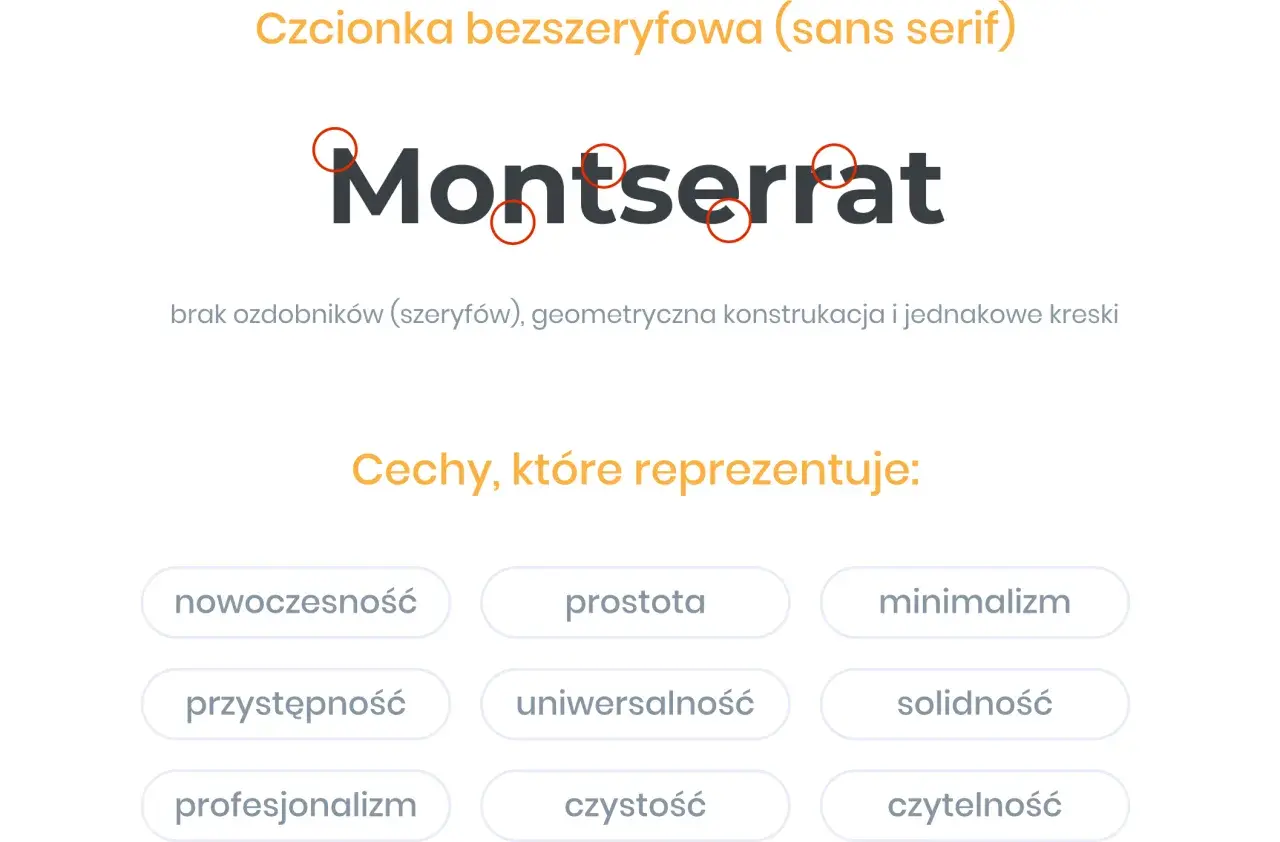
Typografia może podnieść wiarygodność marki albo osłabić ją w kilka sekund. W reklamie lokalnej, na stronie firmowej czy w menu restauracji decyduje nie tylko treść, ale też to, jak litery prowadzą wzrok i czy komunikat da się odczytać bez wysiłku. W praktyce właśnie od tego zależy dobór kroju czcionki, a nie od samego gustu projektanta. W tym tekście rozkładam temat na konkretne części: czym jest krój pisma, jak wpływa na odbiór marki, jak dobrać go do nośnika i jak uniknąć błędów, które psują czytelność.
Najważniejsze rzeczy, które warto wiedzieć, zanim wybierzesz krój do projektu
- Krój pisma nadaje tekstowi charakter, ale musi przede wszystkim pozostać czytelny.
- W reklamie lokalnej najlepiej sprawdzają się zwykle proste, wyraźne fonty z dobrą rozpoznawalnością w małym formacie.
- Jedna marka rzadko potrzebuje więcej niż 2 kroje w tym samym projekcie.
- Na ekranie i w druku obowiązują inne warunki, więc ten sam projekt trzeba oceniać osobno w obu środowiskach.
- Najczęstszy błąd to wybieranie efektownych liter kosztem szybkości odczytu.
Czym różni się krój pisma od fontu i dlaczego to ma znaczenie
W codziennym języku te pojęcia często się mieszają, ale w typografii różnica jest przydatna. Krój pisma to zaprojektowany zestaw liter o wspólnej stylistyce, natomiast font jest jego konkretną cyfrową odmianą, na przykład w określonej grubości, wersji i formacie pliku. Dla osoby zamawiającej reklamę nie jest to akademicki detal, tylko praktyczna wskazówka: wybierasz nie „ładne literki”, lecz narzędzie, które ma działać w konkretnym miejscu i rozmiarze.
Warto też pamiętać, że w projektach marketingowych liczy się cały system typograficzny, a nie pojedyncza nazwa fontu. Ten sam krój może wyglądać dobrze w nagłówku, ale fatalnie w małym akapicie. Inny świetnie sprawdzi się na wizytówce, lecz na szyldzie okaże się zbyt delikatny. Gdy rozumiesz tę różnicę, łatwiej podejmujesz decyzje, które nie kończą się poprawkami po wydruku.
To prowadzi do najważniejszego pytania: jaki efekt ma wywołać tekst, zanim jeszcze ktokolwiek zacznie go czytać?
Jak typografia zmienia odbiór marki i reklamy
Typografia nie tylko „ładnie wygląda”. Ona komunikuje tempo, ton i poziom formalności. Krój z szeryfami może budować skojarzenie z tradycją, zaufaniem i stabilnością, a prosty bezszeryfowy zwykle brzmi nowocześniej, czyściej i bardziej neutralnie. To nie są sztywne reguły, ale w praktyce często działają właśnie tak, szczególnie gdy odbiorca widzi projekt tylko przez kilka sekund.
W reklamie lokalnej to ma ogromne znaczenie. Inaczej projektuje się komunikat dla kancelarii, inaczej dla salonu beauty, a jeszcze inaczej dla warsztatu samochodowego czy kawiarni. Na witrynie czy banerze przy ruchliwej ulicy czytelność wygrywa z ozdobnością. Z kolei w logo albo krótkim haśle można pozwolić sobie na więcej charakteru, o ile nie psuje to rozpoznawalności.
Ja zwykle zaczynam od pytania, co klient ma poczuć po pierwszym kontakcie z marką: bezpieczeństwo, energię, prestiż, a może po prostu prostotę. Dopiero potem dobieram krój, bo litery nie są dekoracją oderwaną od przekazu. Są jego częścią.
Gdy ta zależność jest jasna, łatwiej przejść od ogólnej teorii do konkretnych rodzajów krojów i ich zastosowań.
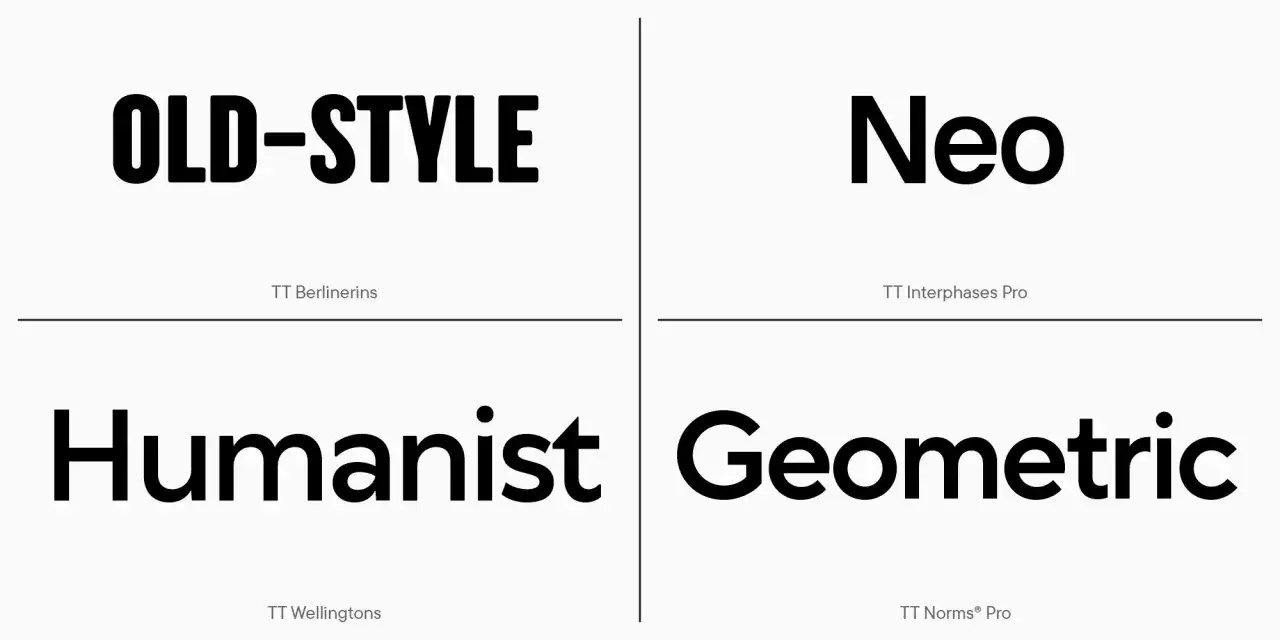
Rodzaje krojów i kiedy każdy z nich ma sens
Najprościej podzielić kroje według ich charakteru i sposobu użycia. W praktyce nie chodzi o to, by znać wszystkie nazwy, tylko wiedzieć, czego się po nich spodziewać.
| Rodzaj | Jak wygląda | Kiedy działa najlepiej | Na co uważać |
|---|---|---|---|
| Szeryfowy | Ma drobne zakończenia przy literach, wygląda bardziej klasycznie. | Marki premium, treści redakcyjne, komunikacja oparta na zaufaniu i tradycji. | W małych rozmiarach lub przy niskiej jakości druku może tracić wyrazistość. |
| Bezszeryfowy | Jest prostszy, czystszy i często bardziej geometryczny. | Strony internetowe, social media, szyldy, ulotki i komunikaty usługowe. | Przy źle dobranej grubości bywa zbyt neutralny i „bez twarzy”. |
| Płytowy | Ma masywniejsze szeryfy, daje mocny, stabilny efekt. | Nagłówki, reklamy z charakterem, marki, które chcą wyglądać solidnie. | W długim tekście może męczyć wzrok, jeśli jest zbyt ciężki. |
| Skryptowy | Naśladuje pismo odręczne, bywa elegancki lub romantyczny. | Logotypy, zaproszenia, pojedyncze hasła, elementy dekoracyjne. | W dłuższym tekście prawie zawsze przegrywa z czytelnością. |
| Display | Stworzony do przyciągania uwagi, często ma mocny charakter. | Plakaty, kampanie sezonowe, krótkie hasła, grafiki promocyjne. | To krój „na efekt”, więc łatwo przesadzić i przeciążyć projekt. |
| Monospace | Każda litera zajmuje podobną szerokość, wygląda technicznie. | Elementy kojarzone z technologią, kodem, danymi lub nowoczesnym minimalizmem. | W marketingu trzeba go używać oszczędnie, bo szybko dominuje kompozycję. |
Jeśli miałbym wskazać najbezpieczniejszy punkt startu dla lokalnej firmy, wybrałbym prosty bezszeryfowy krój do treści i ewentualnie mocniejszy wariant do nagłówków. Z kolei dekoracyjne litery zostawiłbym do krótkich akcentów, bo ich siła polega na tym, że pojawiają się rzadko. Im krótszy komunikat, tym większą swobodę można sobie pozwolić.
Sam wybór typu to jednak dopiero początek. Prawdziwa różnica wychodzi dopiero wtedy, gdy dopasujesz go do medium, odległości i długości tekstu.
Jak dobrać krój do ulotki, strony i szyldu krok po kroku
Przy wyborze kroju pracuję zawsze od strony użycia, a nie od strony gustu. To prostsze i zwykle skuteczniejsze.
-
Określ nośnik i dystans czytania.
Tekst na stronie internetowej ogląda się z bliska, a szyld lub baner z ulicy. To oznacza inne wymagania wobec grubości liter, kontrastu i odstępów. Na ekranie treść podstawowa zwykle dobrze pracuje w okolicach 16–18 px, a na nośnikach drukowanych trzeba patrzeć przede wszystkim na realny rozmiar po wydruku, nie na samą liczbę w projekcie.
-
Oddziel nagłówek od tekstu użytkowego.
Nagłówek może mieć więcej charakteru, ale akapit powinien pozostać maksymalnie czytelny. Jeśli cały projekt wygląda tak samo, odbiorca nie wie, gdzie patrzeć najpierw. Dobra hierarchia typograficzna prowadzi wzrok bez wysiłku.
-
Sprawdź interlinię i długość wiersza.
Interlinia to odstęp między wierszami. Zbyt mała męczy, bo litery się zlewają, a zbyt duża rozrywa akapit. W praktyce bezpieczny punkt startu to około 1,4–1,7 wysokości kroju. Z kolei zbyt długie wersy utrudniają czytanie, więc w treściach internetowych dobrze trzymać się mniej więcej 45–75 znaków w wierszu.
-
Ogranicz liczbę krojów i wariantów.
Dwie rodziny w jednym projekcie najczęściej wystarczą. Trzecia zwykle wprowadza chaos, chyba że ma bardzo konkretną funkcję, na przykład do wyróżnienia cytatu albo liczby promocyjnej. Większy problem niż sama liczba rodzin robią też przypadkowo dobrane grubości i zbyt mocne kontrasty stylistyczne.
-
Testuj projekt w realnym użyciu.
To, co wygląda dobrze na dużym monitorze, może okazać się słabe na telefonie albo w druku niskiej jakości. Wydruk próbny i szybki test na ekranie telefonu pokazują więcej niż godzina w katalogu fontów. Ja zawsze sprawdzam projekt w warunkach zbliżonych do końcowych, bo wtedy od razu widać prawdziwe problemy.
Jeśli ten etap przeprowadzisz uczciwie, od razu wyjdą też ograniczenia projektu. A właśnie one najczęściej obnażają słabe decyzje typograficzne.
Najczęstsze błędy, które psują nawet dobry projekt
Nawet dobry krój można zepsuć złym użyciem. W marketingu lokalnym widzę to regularnie, bo projekt robi się szybko, a typografia dostaje mniej uwagi niż zdjęcia czy kolory.
- Za cienkie litery w małym rozmiarze albo na jasnym, kontrastowym tle. Na ekranie mogą wyglądać elegancko, ale w praktyce znikają.
- Zbyt dekoracyjny font użyty do dłuższego tekstu. Działa w nagłówku, ale męczy, gdy musi udźwignąć kilka zdań.
- Za dużo rodzin krojów w jednym projekcie. Efekt jest chaotyczny, nawet jeśli każda pojedyncza decyzja wydaje się ciekawa.
- Brak polskich znaków. To nadal się zdarza i od razu obniża jakość całej realizacji. Jeśli font nie obsługuje ą, ć, ę, ł, ń, ó, ś, ź i ż, lepiej go od razu odrzucić.
- Złe odstępy między literami, czyli kerning. Kerning to dopasowanie przerw między konkretnymi parami znaków; przy logo i nagłówkach robi ogromną różnicę.
- Ignorowanie kontrastu między tekstem a tłem. Nawet świetny krój nie obroni się na źle dobranym kolorze.
Najuczciwszy test jest prosty: jeśli odbiorca ma się zatrzymać i czytać, tekst musi być łatwy do odczytania w 2–3 sekundy. Jeśli potrzebuje więcej czasu, projekt jest zbyt ciężki albo zbyt ozdobny. To nie jest kwestia stylu, tylko użytkowości.
Gdy te pułapki są nazwane wprost, ostatni krok polega już tylko na zebraniu wszystkiego w praktyczny system dla marki.
Typografia, która naprawdę wspiera lokalną markę
Najlepiej działają rozwiązania proste, ale konsekwentne. W małej firmie nie potrzebujesz rozbudowanej biblioteki fontów, tylko zestawu, który da się powtarzać na stronie, w poście, na wizytówce i na szyldzie. Jeden krój do treści, drugi do nagłówków i jasno opisane zasady użycia zwykle robią większą różnicę niż kolejne eksperymenty.
Jeśli chcesz podejść do tematu praktycznie, zwracaj uwagę na trzy rzeczy: czytelność, spójność i legalność użycia. Licencja fontu bywa pomijana, a przy projektach komercyjnych ma znaczenie równie duże jak wygląd liter. Dobrze jest też zapisać w jednym miejscu podstawowe decyzje typograficzne: rozmiar nagłówka, grubość tekstu, interlinię i dopuszczalne warianty.
Dobrze dobrany krój nie ma krzyczeć. Ma sprawić, że klient szybciej zrozumie ofertę, marka będzie wyglądała pewniej, a komunikat da się przeczytać bez walki ze wzrokiem. Właśnie taka typografia sprzedaje lepiej niż najbardziej efektowny, ale męczący font.